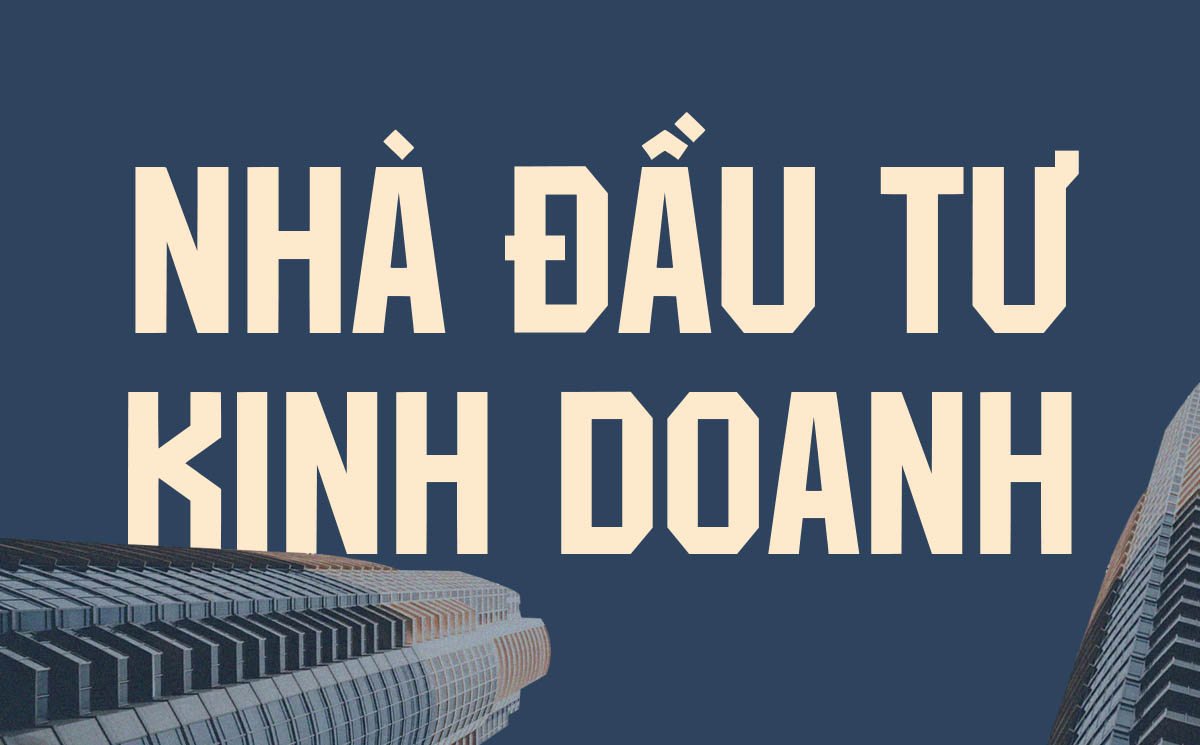
Font chữ cứng cáp miễn phí phong cách mạnh mẽ
font chữ cứng cáp
Font chữ cứng cáp là font có nét thẳng, góc vuông với phong cách mạnh mẽ, masculine được sử dụng rộng rãi trong thiết kế bao bì sản phẩm công nghiệp, túi giấy thương hiệu thể thao và in ấn cho brand nam tính. Font chữ cứng việt hóa với đặc điểm bold, strong tạo cảm giác quyết đoán, powerful.
Ở bài viết này, In Viva giới thiệu font cứng việt hóa với hơn 10 mẫu miễn phí từ Google Fonts phù hợp cho thiết kế bao bì và in ấn mạnh mẽ.
Font chữ cứng cáp là gì?
Font chữ cứng cáp là font có nét thẳng, góc vuông (90 độ), bold weight – ngược lại với font mềm mại có nét cong, flowing. Cứng cáp về structure (straight lines) và weight (heavy, bold).
Đặc điểm font cứng cáp:
• Nét thẳng chiếm ưu thế: Ưu tiên đường thẳng hơn đường cong – chữ I, H, L hoàn toàn thẳng, chữ O gần vuông.
• Góc vuông sắc: Không bo tròn, giữ nguyên góc 90 độ – tạo cảm giác cứng rắn, quyết đoán.
• Bold weight: Thường ở weight Bold (700) trở lên – nét dày tạo impact mạnh.
• Condensed thường gặp: Nhiều font cứng là condensed (hẹp) – tạo cảm giác cao, mạnh mẽ.
Phân loại font cứng cáp:
• Industrial sans: Sans-serif vuông, bold, industrial. Ví dụ: Oswald, Anton, Bebas Neue. Cảm giác: factory, machinery, construction.
• Slab serif: Serif với chân dày như nét chính. Ví dụ: Rockwell, Roboto Slab. Cảm giác: strong, stable, mechanical.
• Display bold: Font display với weight cực đậm. Ví dụ: Black Ops One, Ultra. Cảm giác: powerful, commanding, aggressive.
• Geometric square: Geometric với góc vuông không bo. Ví dụ: Rajdhani, Orbitron. Cảm giác: tech, futuristic, rigid.
Oswald
Condensed sans, bold industrial Poster thể thao, standee gym, banner event
Anton
Condensed black, impact Logo automotive, bao bì công cụ
Bebas Neue
Condensed, versatile bold Tiêu đề poster, brochure industrial
Black Ops One
Display black ultra bold Logo military style, tactical gear
Rajdhani
Geometric square modern Bao bì machinery, catalogue tech
Saira Condensed
Condensed bold, 9 weights Brochure construction, poster event
Teko
Condensed square, sharp Logo sports brand, jersey number
Barlow Condensed
Condensed modern, 18 weights Versatile cho mọi in ấn bold
Roboto Condensed
Condensed neo-grotesque Catalogue automotive, tech spec
Lưu ý: Font cứng mạnh mẽ nhưng khó đọc ở body text. Chỉ nên dùng cho tiêu đề, logo, call-to-action. Body text nên dùng regular weight sans-serif thông thường.
Ứng dụng font cứng trong bao bì nam tính
Font chữ cứng cáp với phong cách powerful được ưa chuộng:
• Perfect cho masculine products: Sản phẩm nam (grooming, cologne, apparel), thể thao, outdoor – font cứng tạo connection với target male audience.
• Industrial, heavy-duty: Công cụ, máy móc, automotive, construction – font cứng gợi liên tưởng đến sức mạnh, độ bền, reliability.
• Sports, fitness, performance: Gym, protein, athletic wear – font cứng tạo cảm giác strength, power, endurance.
• Bold statement, confidence: Brand muốn tạo impression mạnh mẽ, tự tin, quyết đoán – font cứng là weapon.
Font cứng cáp xuất hiện trong nhiều sản phẩm in ấn:
• Bao bì sản phẩm nam: men’s grooming, cologne, shaving kit, beard oil.
• Túi giấy thể thao: gym brand, athletic wear, sports equipment.
• Bao bì công cụ: power tools, hand tools, hardware, DIY equipment.
• Logo automotive: car detailing, motorcycle brand, auto parts.
• Nhãn sản phẩm outdoor: camping gear, hiking equipment, tactical backpack.
Font chữ cứng cáp mạnh mẽ
1. Khi nào nên dùng font cứng?
Dùng font cứng cho: men’s products (grooming, apparel), sports/fitness, automotive, tools/machinery, outdoor gear, energy drinks. KHÔNG dùng cho beauty, wellness, kids, luxury feminine, organic.
3. Font cứng có nên dùng cho body text không?
Không. Font cứng bold/condensed rất khó đọc ở paragraph dài. Dùng cho tiêu đề, logo, số – body text dùng regular sans như Roboto, Inter.